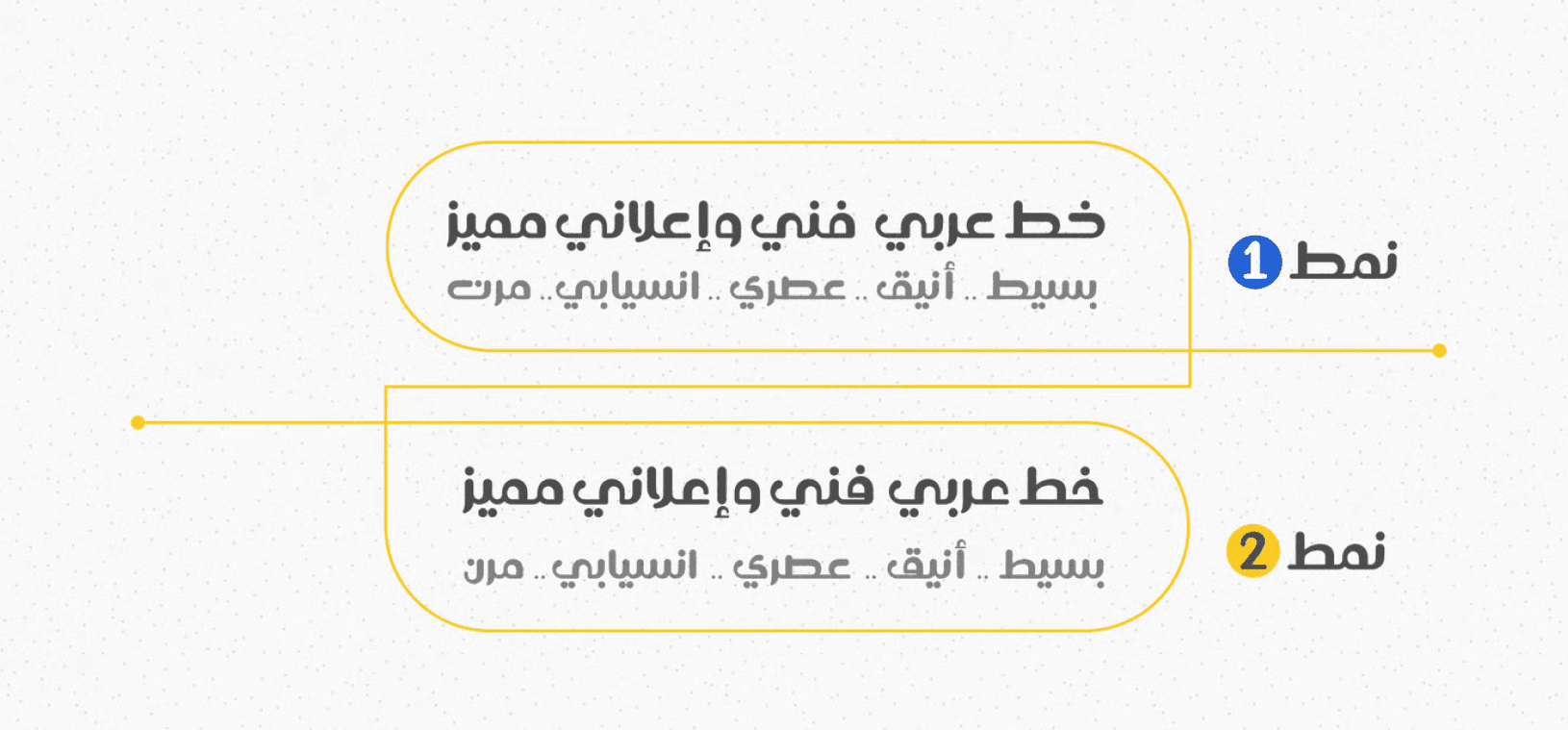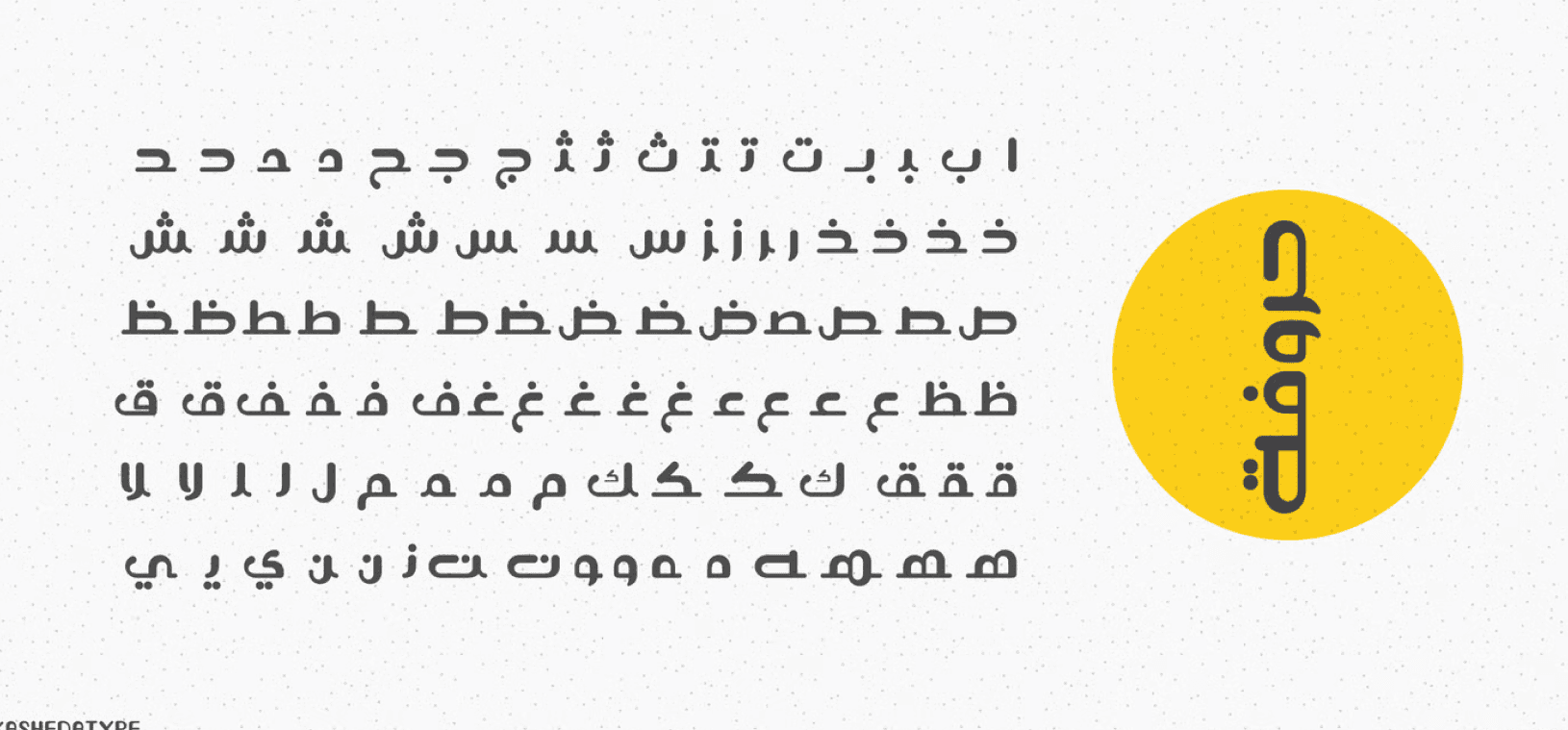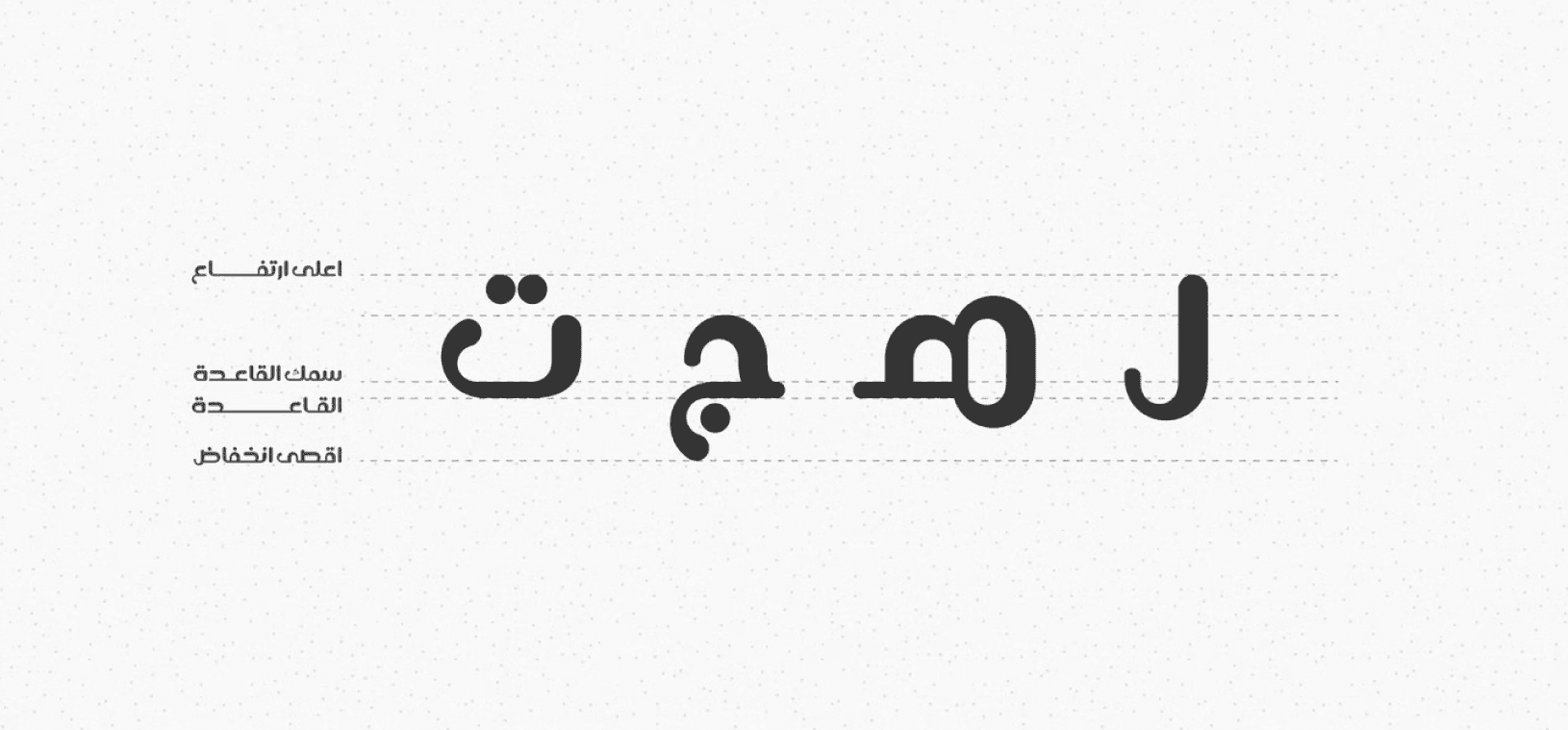
يأتي خط "سبيس" بتصميم هندسي مستوحى من عالم التقنية والفضاء، يجمع بين البساطة والحداثة بأسلوب مرح وانسيابي. يتميز بحروف ناعمة الزوايا وسهلة القراءة، مما يجعله مناسبًا لتصاميم العلامات التجارية، والمطبوعات الحديثة، والتطبيقات الرقمية التي تبحث عن لمسة مستقبلية مميزة. مثالي للعناوين والنصوص التي تتطلب وضوحًا وأناقة في آنٍ واحد.